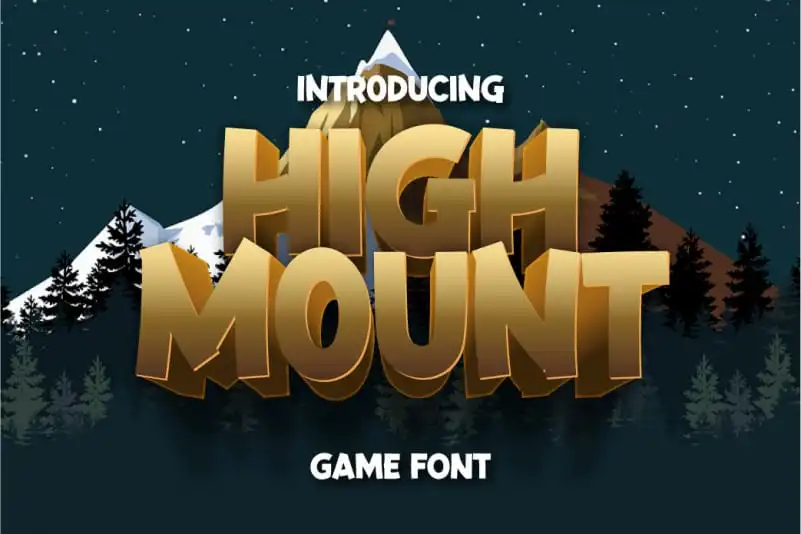
A High Mount Display Font é uma nova abordagem que oferece um estilo moderno e versátil para designers digitais. Com um visual poderoso, sólido e claro, essa fonte adquire uma beleza única ao integrar as diversas obras de design onde for aplicada. O designer twinletter criou algo que se adequa perfeitamente para projetos ambiciosos e inovadores. Seja você um profissional de design ou até mesmo um amante da arte visual, High Mount Display é a escolha certa para criar designs impecáveis com uma personalidade única. Com sua coragem no estilo de destaque e robustez, essa fonte se adapta perfeitamente aos seus projetos, seja ele em logotipos, materiais gráficos ou qualquer outro tipo de projeto que você possa imaginar. Descubra o poder da High Mount Display Font hoje mesmo!